Les bests of de la fonderie Mika Melvas.
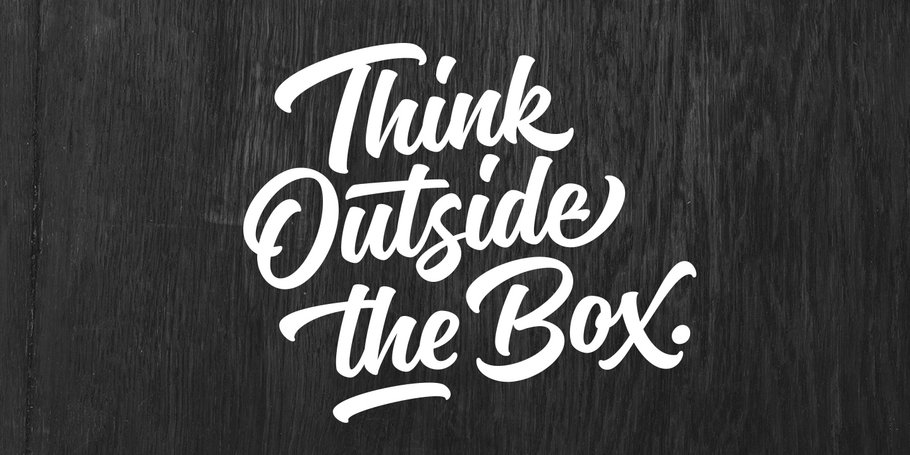
Mika Melvas.
Mika Melvas a commencé sa carrière comme directeur artistique et graphiste dans des agences de publicité et a expérimenté la typographie en parallèle. Suivant sa passion, Mika a travaillé dur pour orienter sa carrière vers une carrière de dessinateur de caractères et de lettrage à plein temps. Sa bibliothèque couvre maintenant une gamme typographique allant des empattements extra gras aux polices de caractères au pinceau, plus ludiques, qui lui sont propres.
Authenia
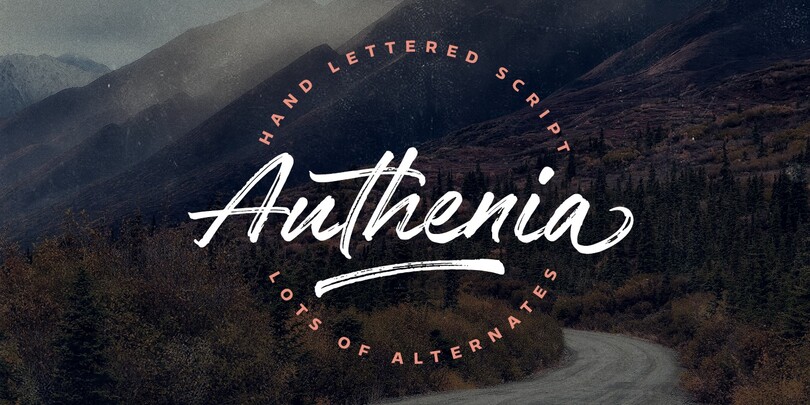
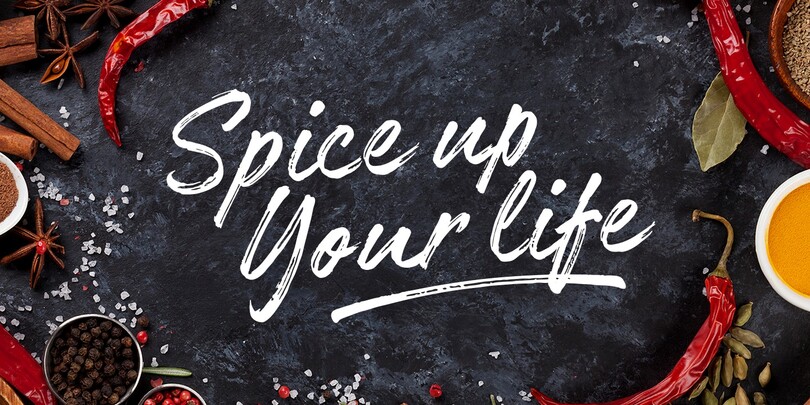
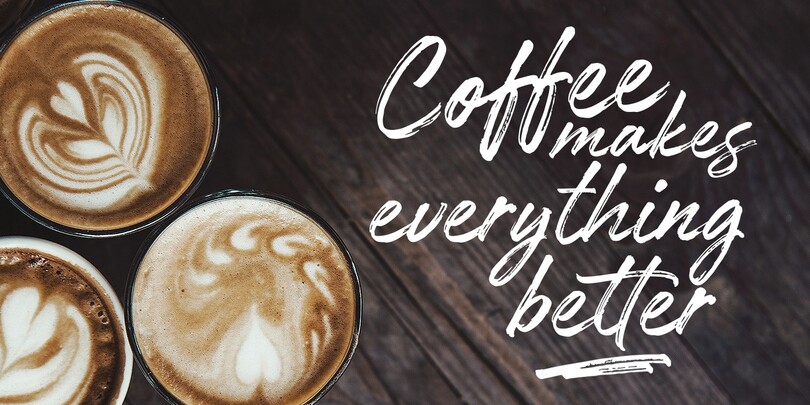
Authenia est une police organique, authentique et décontractée. Elle apparaît de manière désinvolte et rapide, écrit au stylo-brosse sur un papier. Il y a juste la bonne quantité de texture pour que les polices de caractères soient efficaces en petites et grandes tailles !
Fineday
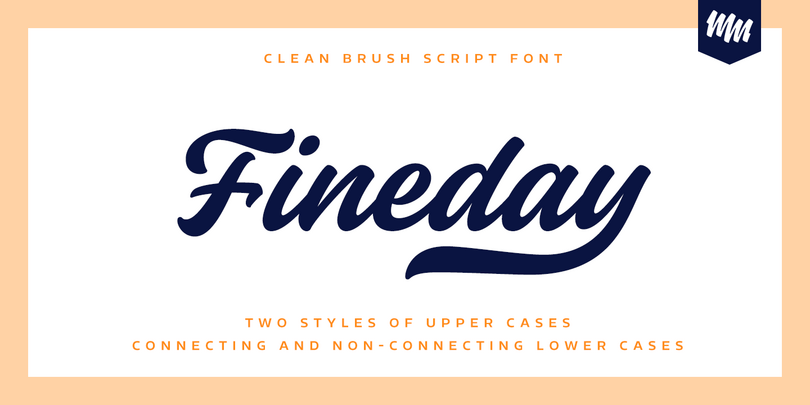
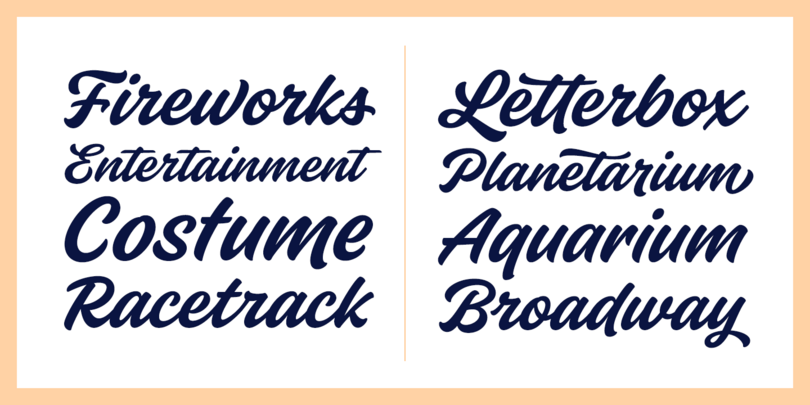
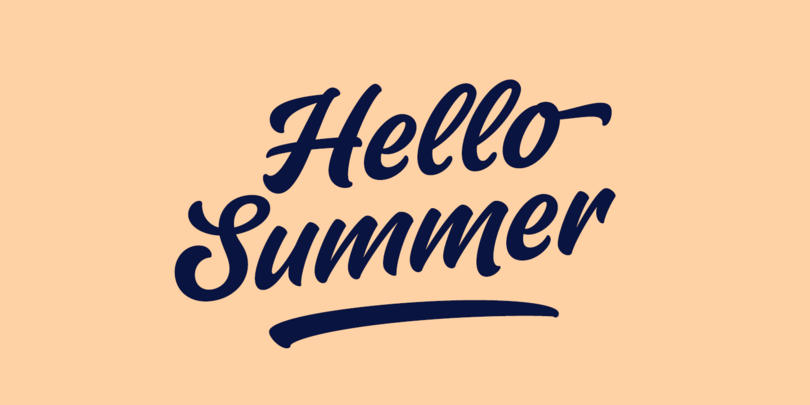
Fineday est une police brush script disponible avec deux styles différents de majuscules : Le premier style est plus swashy et décoratif, tandis que le second est plus simple et direct. Fineday est également disponible avec des jeux de minuscules connectés et non connectés. Toutes les versions de Fineday ont des caractères alternatifs fantaisistes comme des balais de fin, des terminaisons et des ascendants swashy.
Monteria
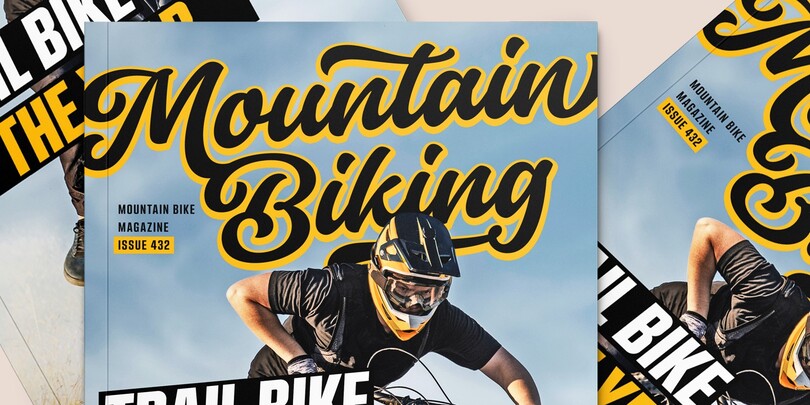
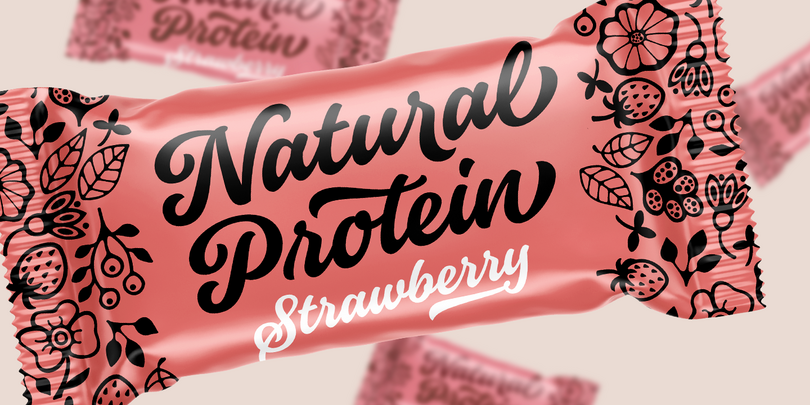
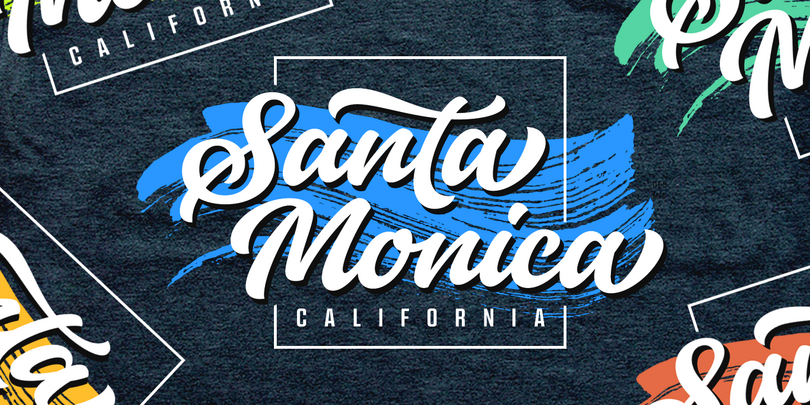
Monteria est une police brush script conçue pour avoir un écoulement facile et des formes douces. Les lettres de base sont conçues pour être simples et lisibles, mais peuvent être habillés avec de nombreuses variantes. Elle convient aux logos, titres, t-shirts, emballages et autres.
Mainsail
Une police brush manuscrite, Mainsail a été écrite avec un stylo à pinceau sec, ce qui lui donne cette belle texture et cette fluidité. Mainsail a beaucoup d’alternatives pour qu’elle ressemble plus à de l’écriture manuscrite réelle ; quatre séries de minuscules et deux séries de majuscules. Mainsail est une excellente option pour les logos, les titres et les emballages. Vous pouvez également l’utiliser pour des textes plus longs, lorsque vous avez besoin d’un style manuscrit décontracté. Elle se combine également bien avec les polices sans et avec empattement.
Handelson
Handelson est une collection de 6 polices de caractères faites à la main avec un toucher authentique et organique. Elle contient trois types d’écriture, une écriture non connectée et deux écritures géométriques sans empattement, toutes en majuscules. Les textures et les bords bruts simulent l’aspect de l’écriture manuscrite et de l’impression. En combinant ces polices, vous pouvez créer des solutions et des éléments typographiques divers avec un style unifié.
Lemonado
Lemonado comprend des écritures romaines droites, italiques et également des polices toutes en majuscules avec une texture de pinceau ou avec des bords lisses. Le script est ludique et légèrement rebondissant. Il comprend deux jeux de minuscules pour augmenter l’effet d’écriture. Grâce à l’alternance contextuelle, vous pouvez faire varier ces deux ensembles pour obtenir un aspect plus naturel. Vous pouvez également activer l’alternance contextuelle pour le style des majuscules, qui comporte deux jeux de majuscules, hautes et basses, pour obtenir un effet de rebondissement.
Bakeshop
Bakeshop est une famille de polices d’écriture décontractée, dessinée avec un marqueur arrondi, produisant un faible contraste. Pour créer un aspect naturel convaincant, elle présente même des bosses à la fin des traits où le stylo s’est arrêté et où l’encre s’est étalée. Bakeshop comprend trois graisses et est disponible en version avec ou sans connexion.
Kaleidos
Kaleidos est une écriture au pinceau avec des formes de lettres douces et rondes. Elle est esquissée et dessinée à l’aide d’un pinceau pointu. Kaleidos comporte de nombreuses alternances, ligatures et ornements, ce qui vous permet de créer des mots et des titres intéressants. Bien que Kaleidos soit condensée et assez serrée, elle est claire et lisible.
Ahkio
Enracinée dans la peinture d’enseignes et le lettrage de cartes de visite des années 1930, Ahkio est une famille de police d’écriture déconnectée et brossée contenant 5 fontes. Ses principales caractéristiques sont des formes douces et arrondies et des tiges un peu courbées. Ahkio est une police conviviale et douce qui convient bien aux titres, emballages, logos et par exemple aux affiches. Ses 5 graisses font de Ahkio une police polyvalente qui vous permet d’ajouter du contraste et de l’intérêt à votre typographie.
Suti
Suti est une police d’écriture décontractée tirée des peintres d’enseignes, avec des majuscules et des minuscules. Conçue à l’origine en 2010, elle a été entièrement redessinée en 2016. Chaque peintre d’enseignes a plus ou moins son propre style de lettrage décontracté. Ces alphabets décontractés sont peints avec rapidité et n’ont pas besoin d’être parfaitement alignés, mais les lettres sont toujours nettes et faciles à lire.
Signalist
Signalist est une police d’écriture à pinceau dynamique et énergique. L’espacement serré, les lettres étroites et les arêtes vives donnent à Signalist son aspect et son caractère distinctifs. Elle convient aux créations qui nécessitent une écriture au caractère contemporain. Vous pouvez l’utiliser sur des logos, des t-shirts, des emballages, comme police de titre… vous choisissez !